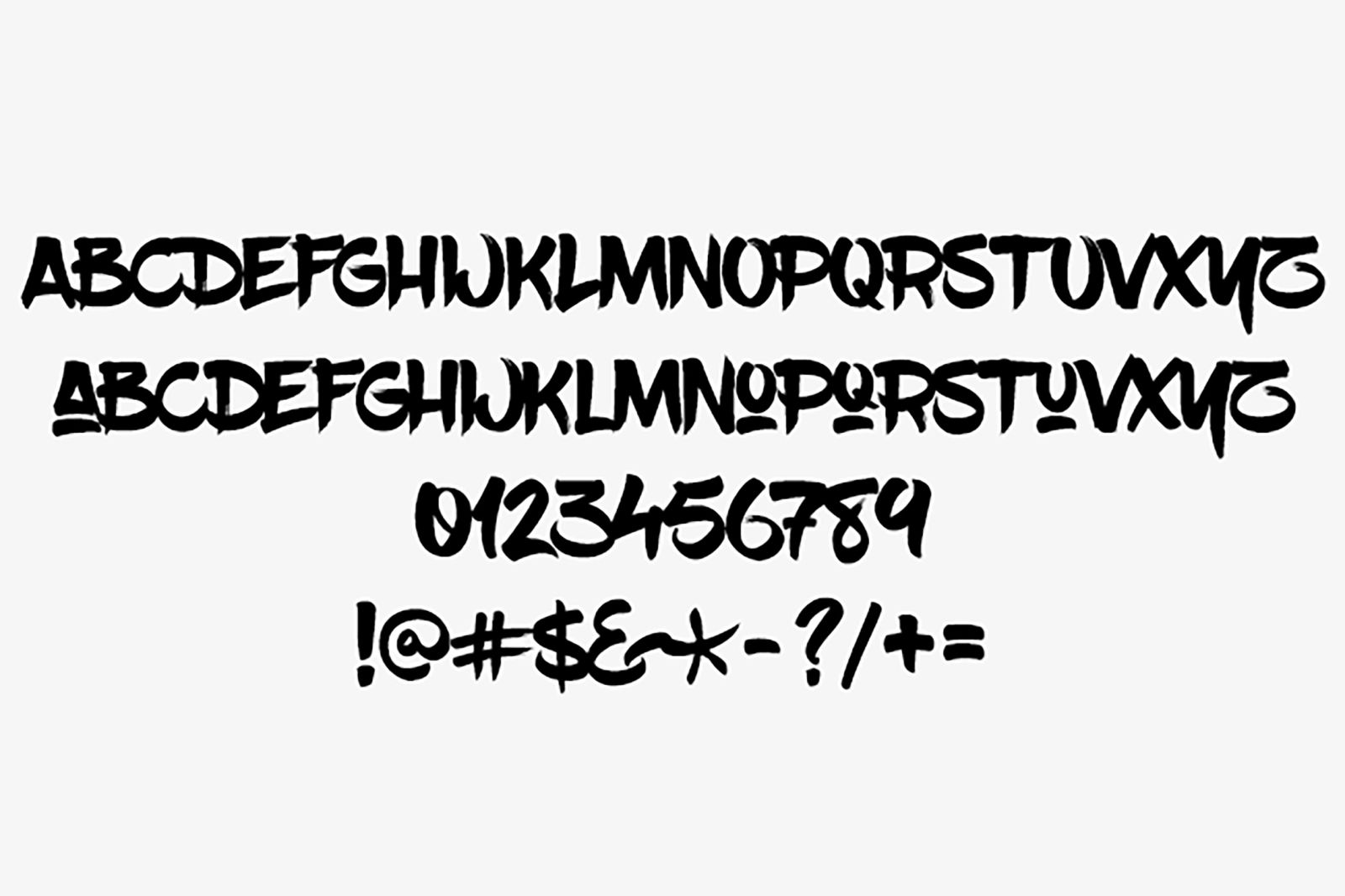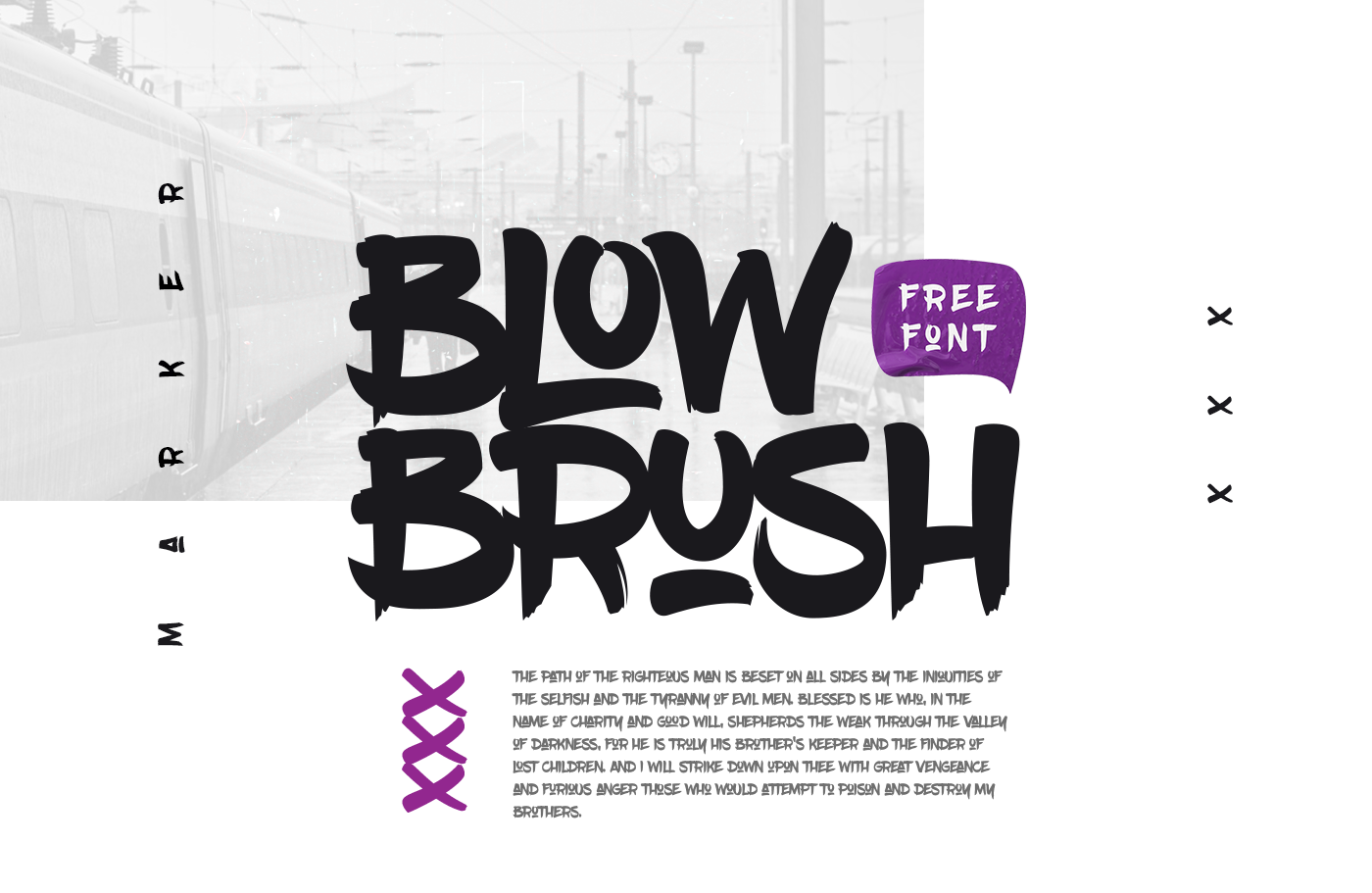
BlowBrush là một phông chữ viết tay theo phong cách đánh dấu với các đường nét và cạnh tự nhiên sẽ mang lại cho văn bản của bạn một ký tự độc đáo và một dòng chảy đẹp, do đó làm cho nó trông nguyên bản. Phông chữ này bao gồm bộ đầy đủ các ký tự hoa, số, 23 chữ ghép, một số ký tự đặc biệt và một số biến thể.